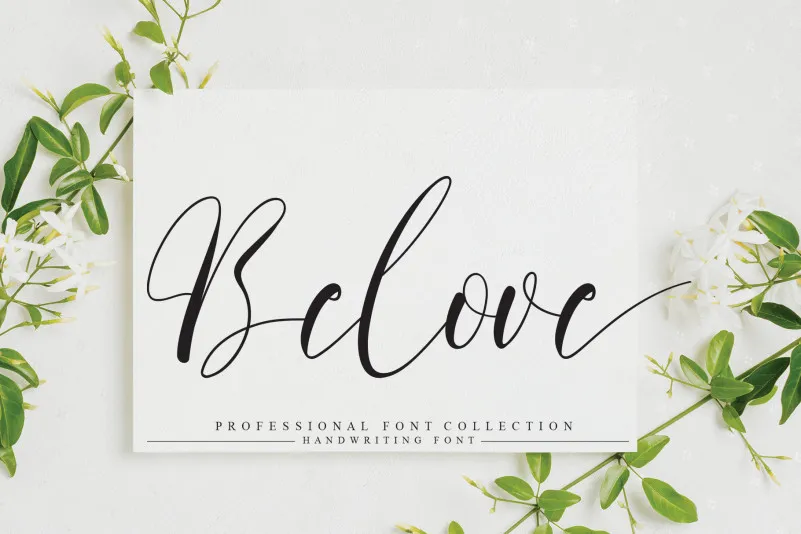
Belove Font – Download Grátis
Esta é uma fonte escrita a mão com estilo moderno e único, criada pelo designer creativeletter. Com seu charme whimsical, ela irá imersão diretamente em um mundo mágico seus designs digitais. Perfeita para incorporar arquétipos de estilo efeitos personalizados em sua identidade visual. Seja você uma marca ou uma criação digital, a Belove Font vai dar o seu design aquele toque especial que faz ele se destacar da concorrência. É uma ótima opção para designers buscam um ar descompromissado e encantador para seus projetos.